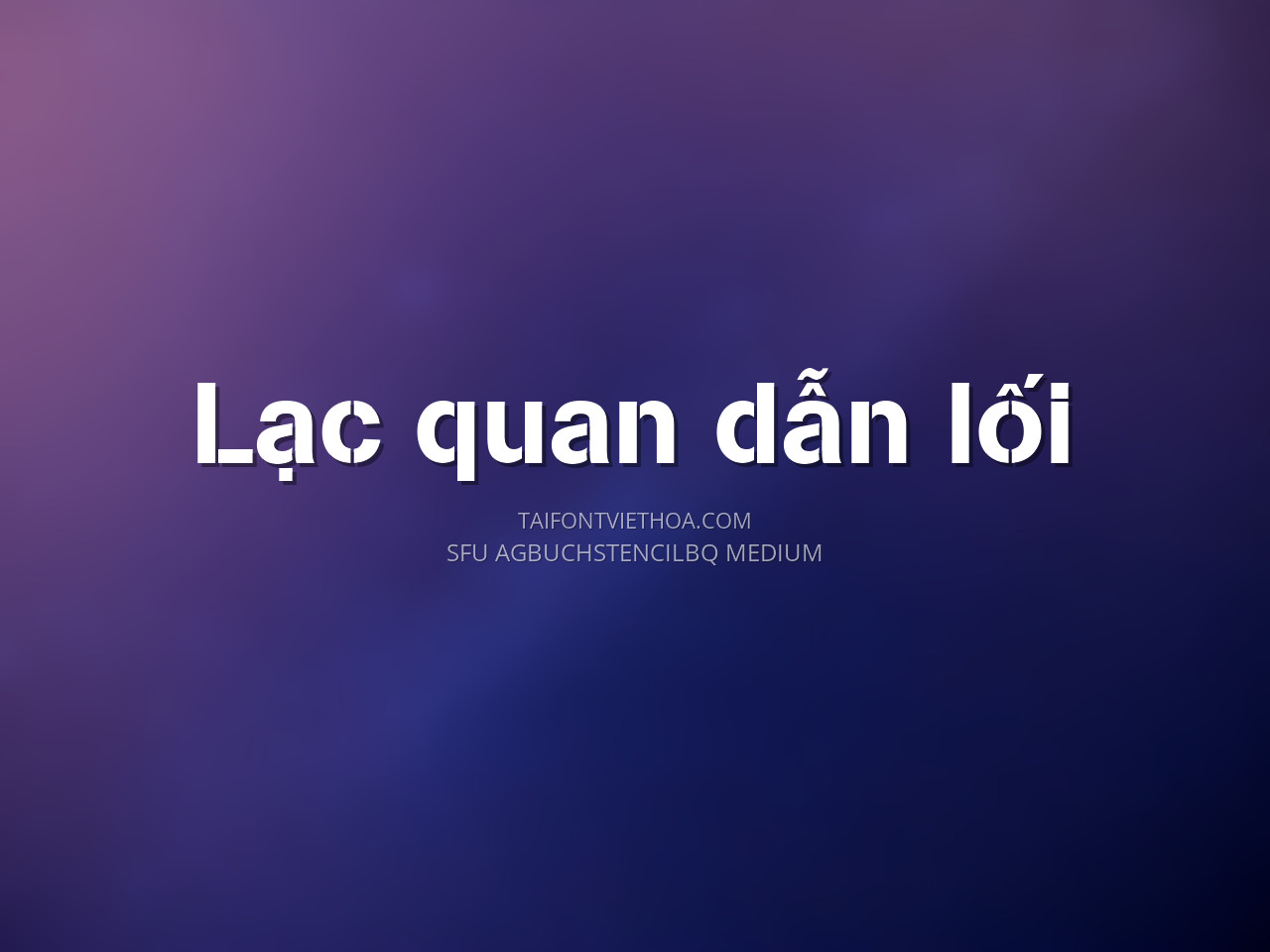
Font việt hóa SFU Agbuchstencilbq
Giới thiệu về font SFU Agbuchstencilbq – Cấu trúc stencil hiện đại và đậm chất công nghiệp
SFU Agbuchstencilbq là phiên bản Việt hóa của font Agbuch Stencil BQ – một kiểu chữ stencil hiện đại được thiết kế theo phong cách công nghiệp, với các đường cắt gọn gàng, mạnh mẽ và mang tính biểu tượng cao. Font stencil thường được sử dụng trong các lĩnh vực kỹ thuật, bao bì công nghiệp, hoặc thiết kế thương hiệu đòi hỏi tính kỹ thuật và độ nhận diện cao. Agbuchstencilbq được phát triển bởi Berthold, một hãng font nổi tiếng của Đức, và nhanh chóng được ứng dụng rộng rãi nhờ sự linh hoạt trong cách thể hiện cá tính và độ rõ ràng thị giác.
Phiên bản SFU Agbuchstencilbq đã được Việt hóa chỉn chu, hỗ trợ đầy đủ bộ dấu tiếng Việt và hơn 60 ngôn ngữ khác. Taifontviethoa.comđã lựa chọn, tinh chỉnh và chia sẻ bộ font này nhằm phục vụ các nhu cầu thiết kế đặc thù như in ấn kỹ thuật, nhận diện thương hiệu công nghiệp, bao bì sản phẩm hoặc thiết kế poster mang hơi hướng kỹ thuật – công nghệ.
Thiết kế stencil rõ ràng – Tối ưu cho kỹ thuật, công nghiệp và nhận diện thương hiệu mạnh
SFU Agbuchstencilbq sở hữu cấu trúc sans-serif stencil với các đường cắt gãy gọn, từng ký tự được phân chia bằng các khe rãnh đặc trưng tạo nên phong cách stencil nguyên bản. Các đường nét được vẽ dứt khoát, độ dày nhất quán, độ tương phản thấp, giúp dễ đọc và nhận diện trong môi trường đòi hỏi độ rõ cao. Font không chỉ mang tính thẩm mỹ mà còn phục vụ tối ưu cho tính năng kỹ thuật và nhận diện trực quan.
Ứng dụng lý tưởng: thiết kế bao bì, biển báo công nghiệp, infographics kỹ thuật, branding ngành cơ khí, poster triển lãm công nghệ, nhận diện công ty sản xuất, các tài liệu kỹ thuật hoặc mô phỏng giao diện quân sự. Ngành nghề phù hợp: sản xuất công nghiệp, cơ khí – điện tử, công nghệ, kiến trúc, logistics và các lĩnh vực liên quan đến kỹ thuật – vận hành.